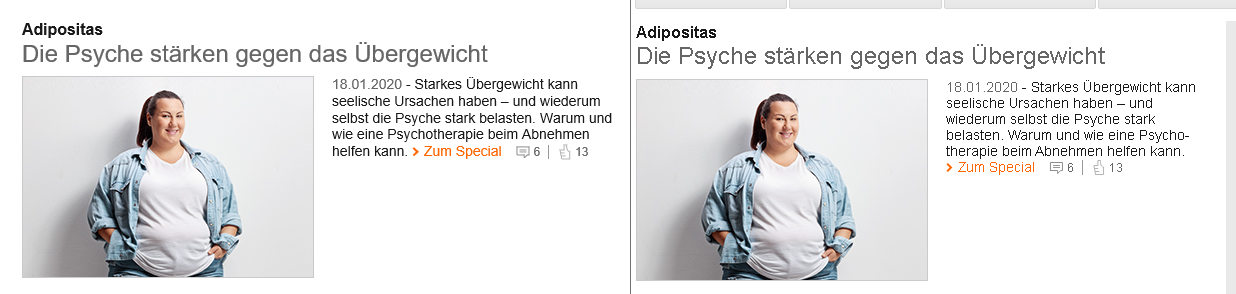
Windows 10 Schriftart in meisten Browsern grausam zu lesen.
in folgenden Browsern wird meine Schriftart zu dünn und schwer lesbar dargestellt:
Chrome, Opera, Firefox, Brave
Nur in den Windows Browsern "Internet Explorer" & "Edge" wird die Schrift normal und schön dick angezeigt.
Da es bei so vielen Browsern nicht richtig dargestellt wird, denke ich es liegt wohl dann an Windows?
Anbei ein Bild zum Vergleich. Links IE und rechts Chrome.. (hoffe man erkennt was ich meine, rechts sieht es "pixelig" und "dünn" aus.)
Das "Problem" kenne ich auch. Bei mir ist allerdings die Darstellung in Firefox am besten, Chrome sieht bei mir von den Schriften her am "dünnsten" aus. Edge fand ich ganz gut. Da er aber künftig die selbe Engine wie Chrome nutzen wird, ist das Thema für mich ebenfalls erledigt.
Danke! An Cleartype hatte ich gar nicht gedacht. Das war die Lösung.
BS und integrierte Browser = Darstelleng Gut.
3. Anbieter Browser = Darstellung Schlecht.
Ergebnis: Windows ist Schuld
Alternativ zu Cleartype Funktion: